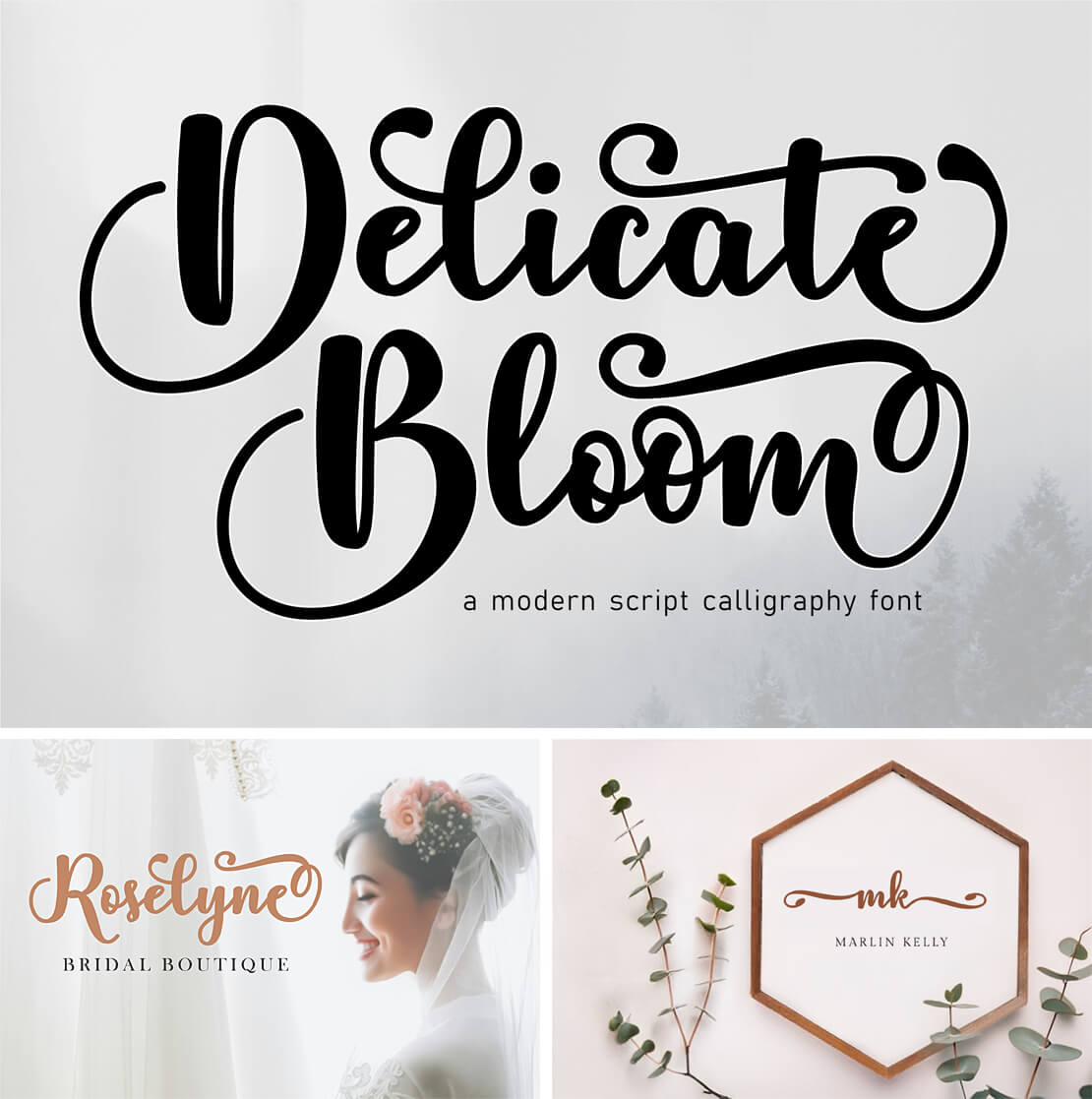
Delicate Bloom
Eine kalligrafische Script-Schriftart aus der Feder von Raffa Creative. »Delicate Bloom« gibt es kostenlos zum Downloaden im Opentype- und TrueType-Format.
Bei diesem Font sind neben deutschen Umlauten auch eine Vielzahl an zusätzlichen Sonderzeichen und Ligaturen enthalten, mit der sich Schriftzüge und Co. individuell mit Schwüngen anpassen oder ergänzen lassen.